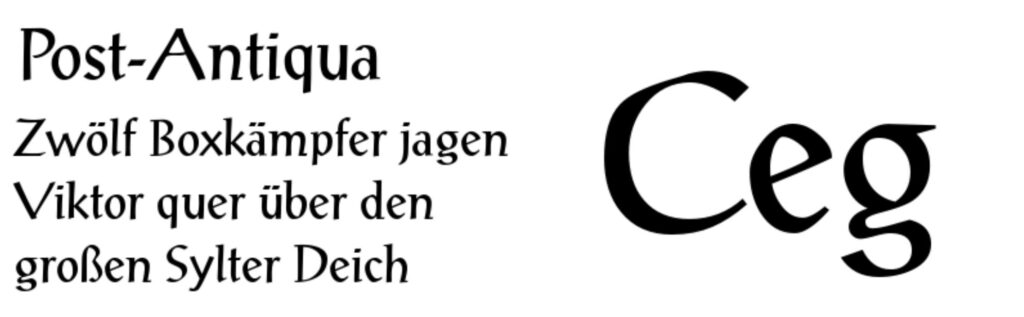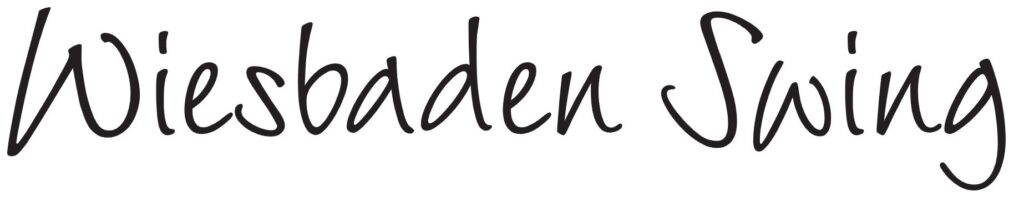
Handschriftliche Antiqua
Diese Schriften sind stärker an individueller Handschrift orientiert als Schreibschriften und wirken dadurch unregelmäßiger und origineller. Sie nähern sich teilweise der Klasse der Schreibschriften an, überschreiten aber deren gleichmäßige Anmutung.
• Merkmale: lockerer, handschriftlicher Charakter, oft unregelmäßiger Rhythmus, dekorative Ausprägung.
• Beispiele: Mistral, Tekton, Vivaldi, Kaufmann, Delphi, Pepita. (Die Mistral wird teils den Schreibschriften, teils den Handschriftlichen Antiqua zugeordnet – ihre betonte Handschriftlichkeit spricht klar für letztere.)